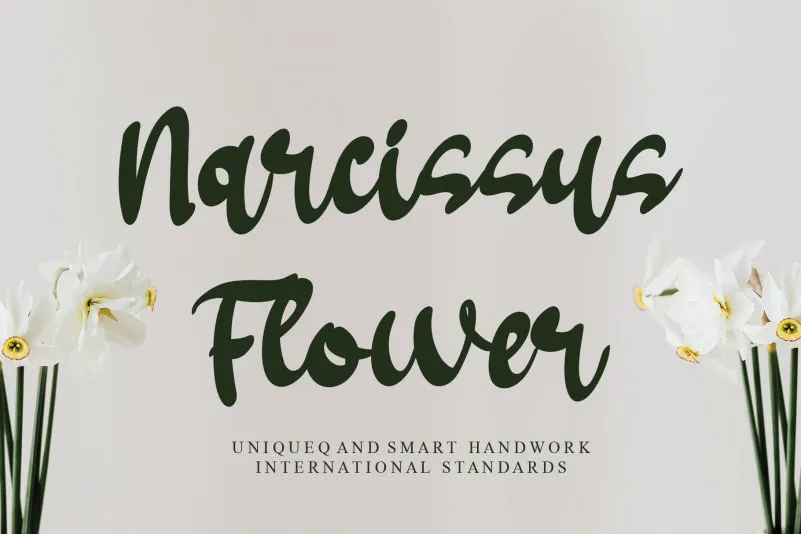
Narcissus Flower Brush Font – Download Grátis
Narcissus Flower Brush Font é uma linda tipografia feita à mão que desfruta de reconhecimento por sua delicadeza e elegância. Este estilo autêntico e moderno se destaca, tornando Narcissus Flower Brush Font um trabalho de arte perfeito para qualquer designer gráfico. Suas formas fluidas e suaves permitem uma versatilidade incrível que o transforma em uma ferramenta versátil para criar designs excepcionais. Seja para um site ou até mesmo para um livro de moda, a Narcissus Flower Brush Font oferece a oportunidade de deixar suas criações ainda mais especializadas e únicas. Com sua característica autêntica de escrita à mão, ela é perfeita para decorar textos com uma sensação nostálgica e delicada. Experimente incorporar Narcissus Flower Brush Font em seu próximo projeto e descubra como essa fonte transforma suas ideias em realidade.